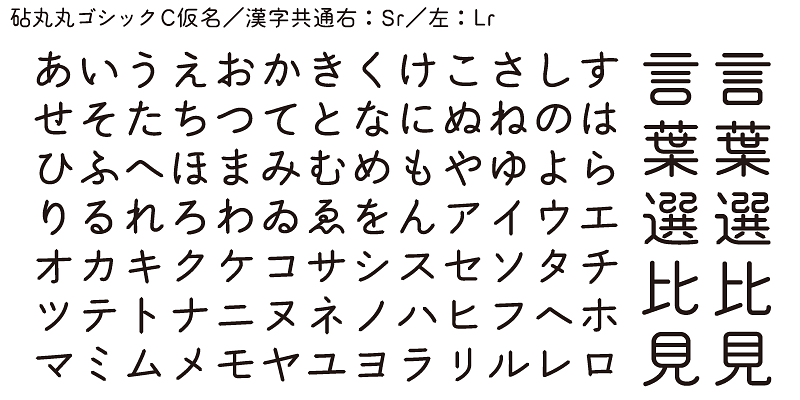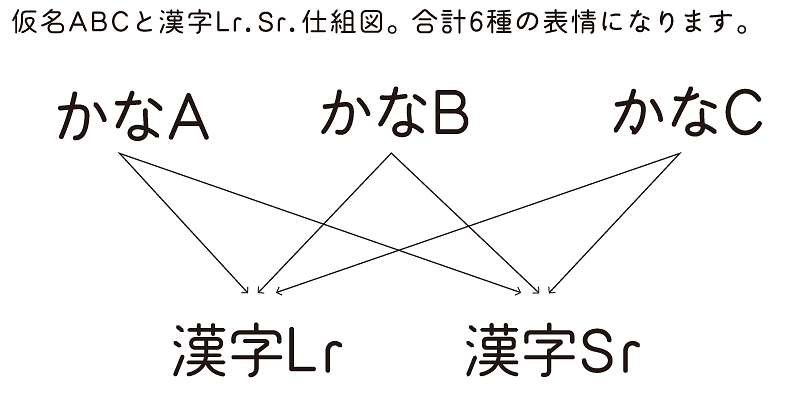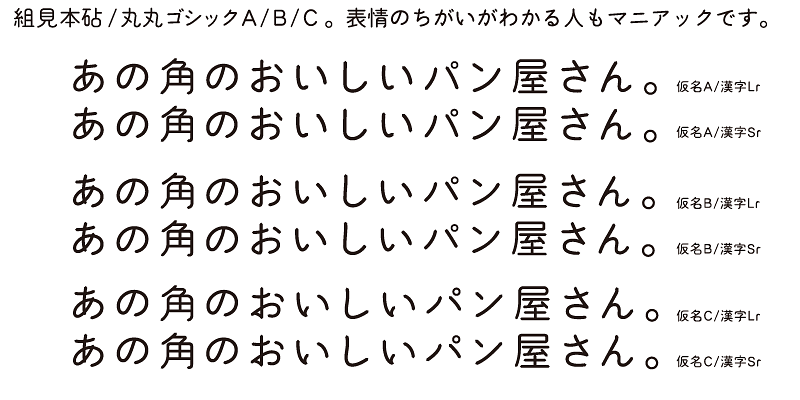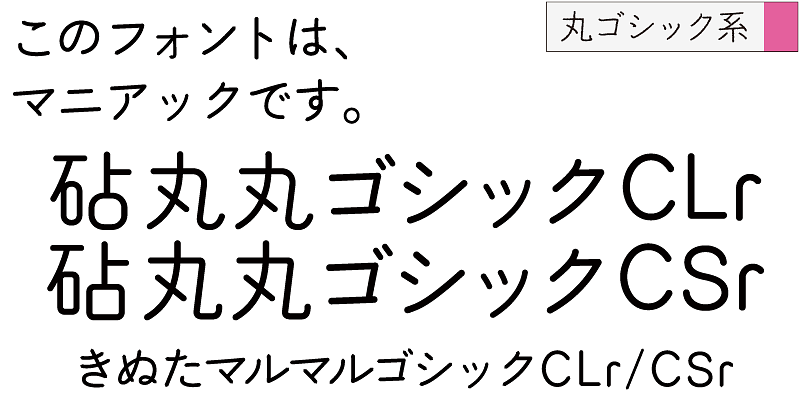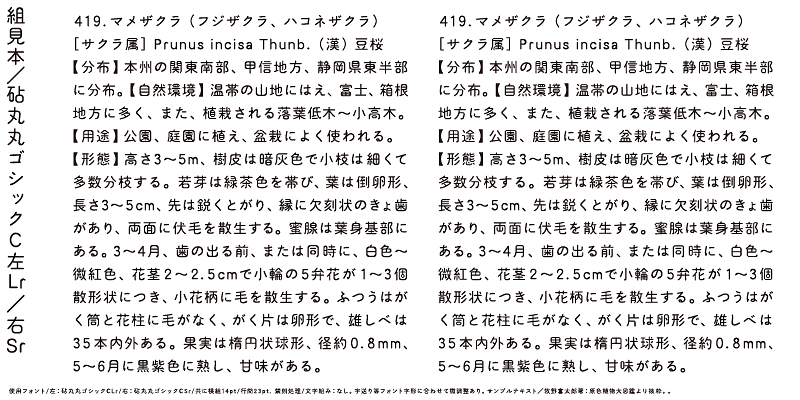
Marumaru Gothic hat zwei Variationen, Sr und Lr, mit kleineren bzw. größeren Eckenrundungen. Die Sr-Variante gibt den Eindruck von Präzision, während Lr eher spontan wirkt. Je nach Textsorte können Sie diese Schriften ruhig mit verschiedenen Kanji-Schriften kombinieren – der Effekt ist außergewöhnlich. Es gibt drei Kana-Stile.
Kana-Stil C ist ruhig mit einem subtilen Hauch von Tradition.
Ein Merkmal der japanischen Sprache sind ihre Kana-Silbenzeichen. Kana-Zeichen wurden in Japan erfunden, um japanische Laute darzustellen und aus China importierte Texte ins Japanische zu übersetzen. Kana-Zeichen werden benötigt, um japanische Wörter und Ausdrücke aus Kanji (chinesischen ideografischen Zeichen) zu erstellen. Auch wenn es Zweideutigkeiten gibt, zeigen diese Wörter und Ausdrücke die Wärme und Sanftheit des Lebens der Menschen, die in dem kleinen und dicht besiedelten Japan leben.
Kinuta Font Factory ist davon überzeugt, dass Kana-Zeichen der Ursprung auf Japanisch geschriebener Wörter sind, und wir glauben, dass die Optimierung von Kana-Zeichen japanische Texte attraktiver macht. Im Durchschnitt bestehen 60 % der japanischen Texte aus Kana-Zeichen – ändert sich die Form dieser Zeichen, verändert das auch das visuelle Erscheinungsbild des Textes. Die Möglichkeiten des typografischen Ausdrucks mit einfachen, dynamischen und kurvenförmigen Kana-Zeichen sind enorm und die Üppigkeit japanischer Texte hängt von Kana-Zeichen ab. Aus diesem Grund bietet Kinuta Font Factory viele Variationen von Kana-Schriftarten an.